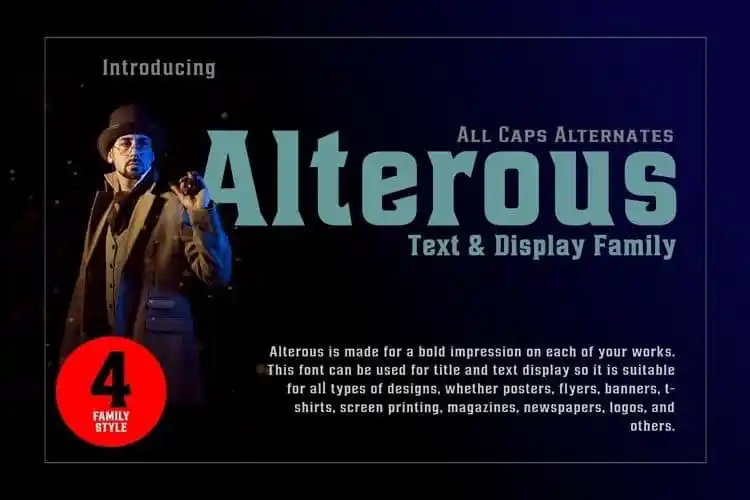
Alterous Display Font – Download Grátis
A Alterous Display Font é uma escolha perfeita para quem busca um gatilho visual poderoso que transmite impacto imediato. Fabricada pela Seventype, essa fonte foi projetada especificamente para criar logomarks e se destacar nos headlines de qualquer obra que seja apresentada. Com seus traços robustos e detalhes arrepiantes, Alterous é perfeito para deixar uma impressão inegável em cada peça de design. Seja ela um postero, folha de papel personalizada, banner ou até mesmo no tênis da sua camiseta, essa fonte está pronta para transformar qualquer texto em um elemento visual atraente e distintivo. Ideal tanto para projetos digitais como impressos, Alterous é uma opção versátil para designers que buscam destacar suas ideias de forma audível e imediata, criando uma ligação emocional entre o design e quem está recebendo a mensagem.